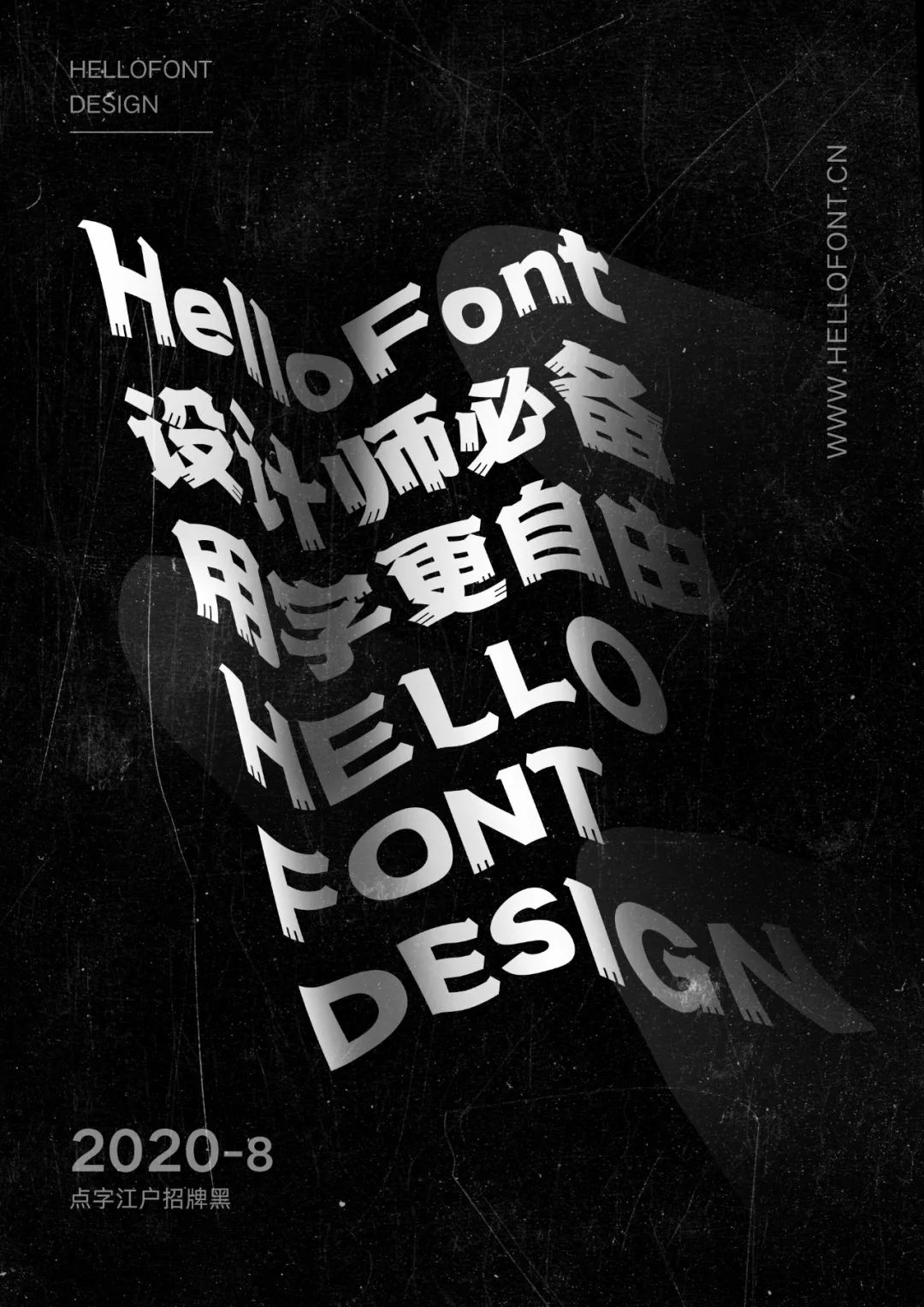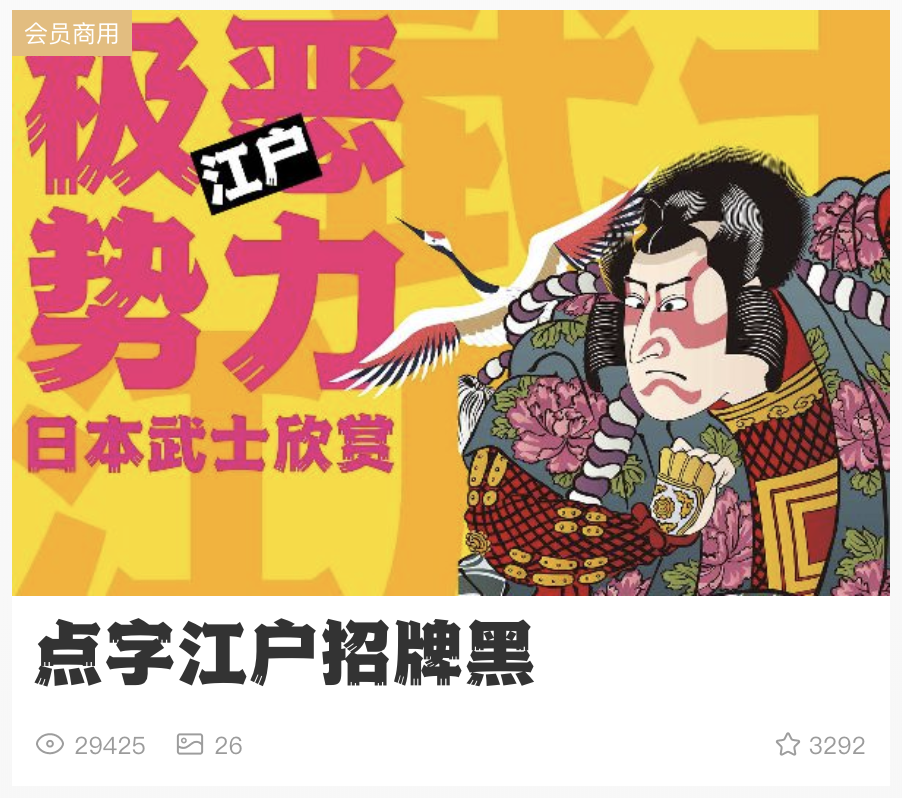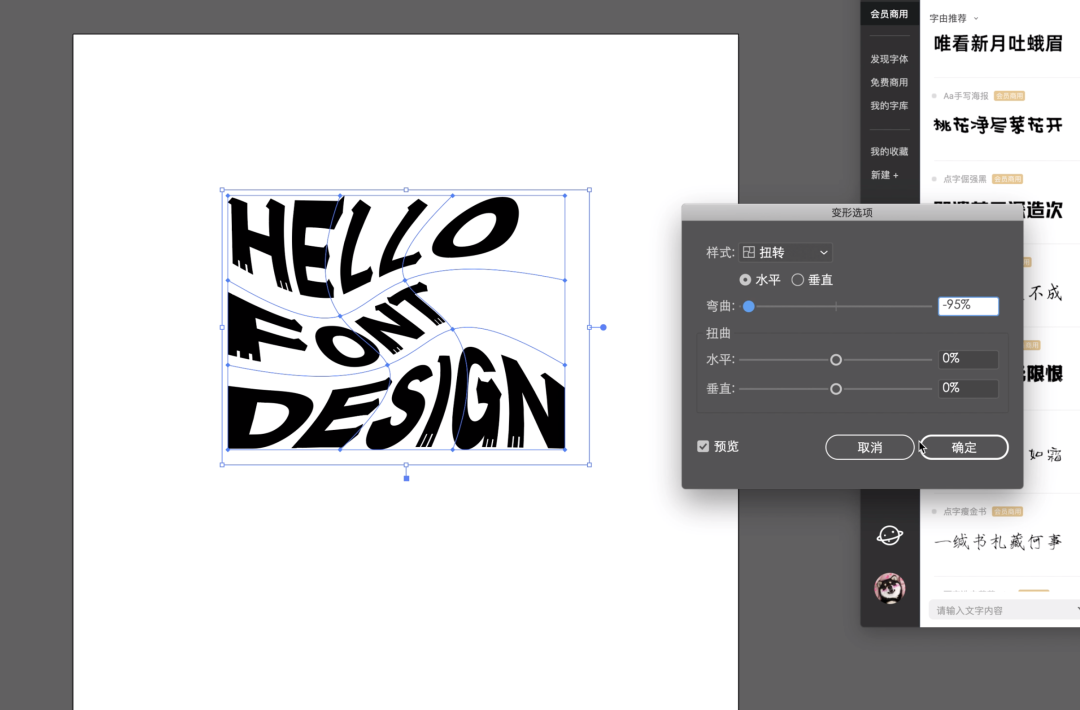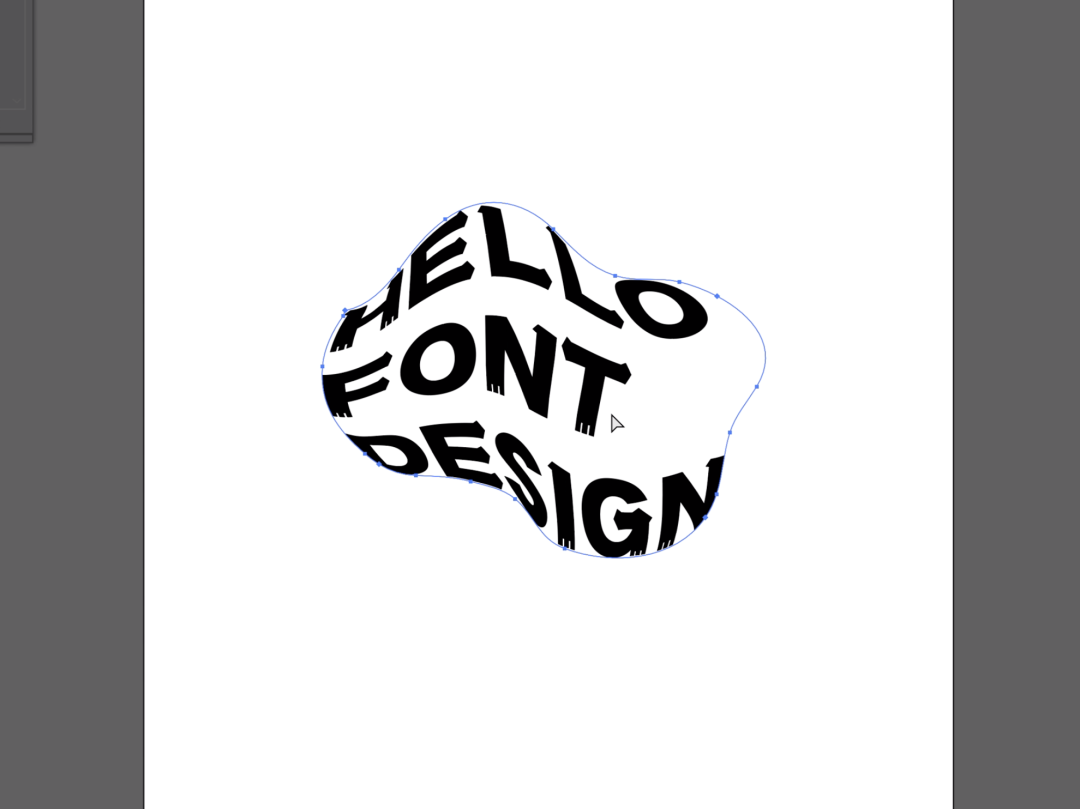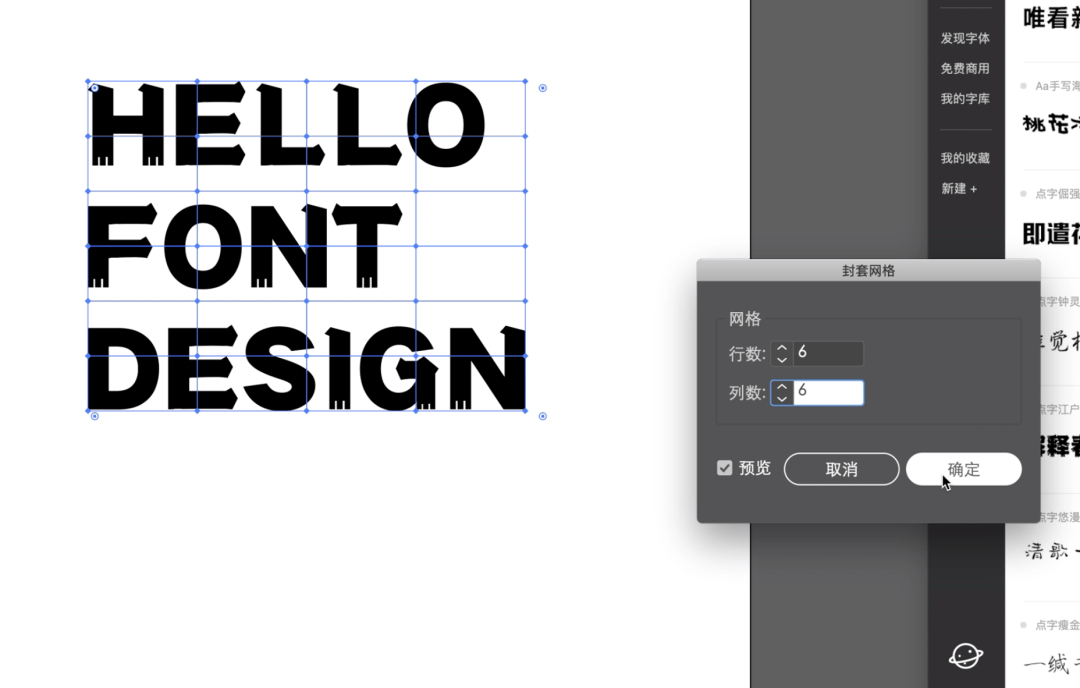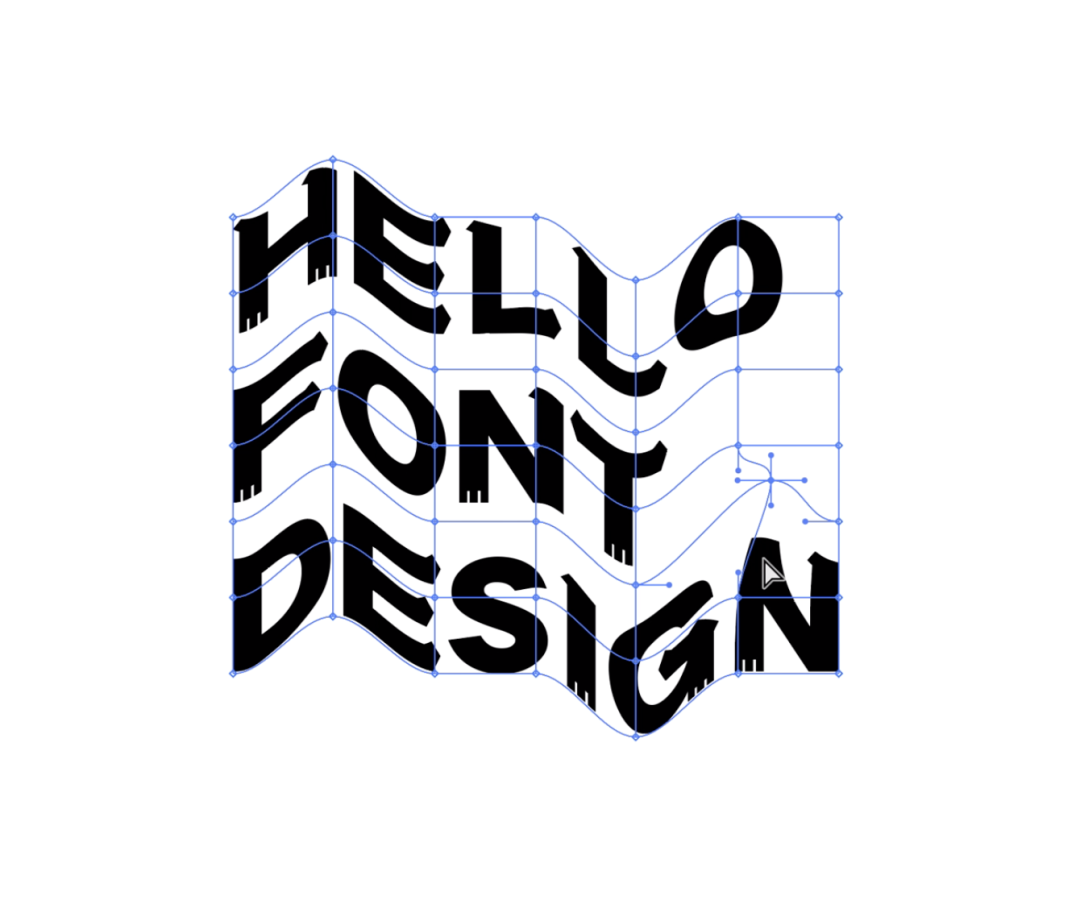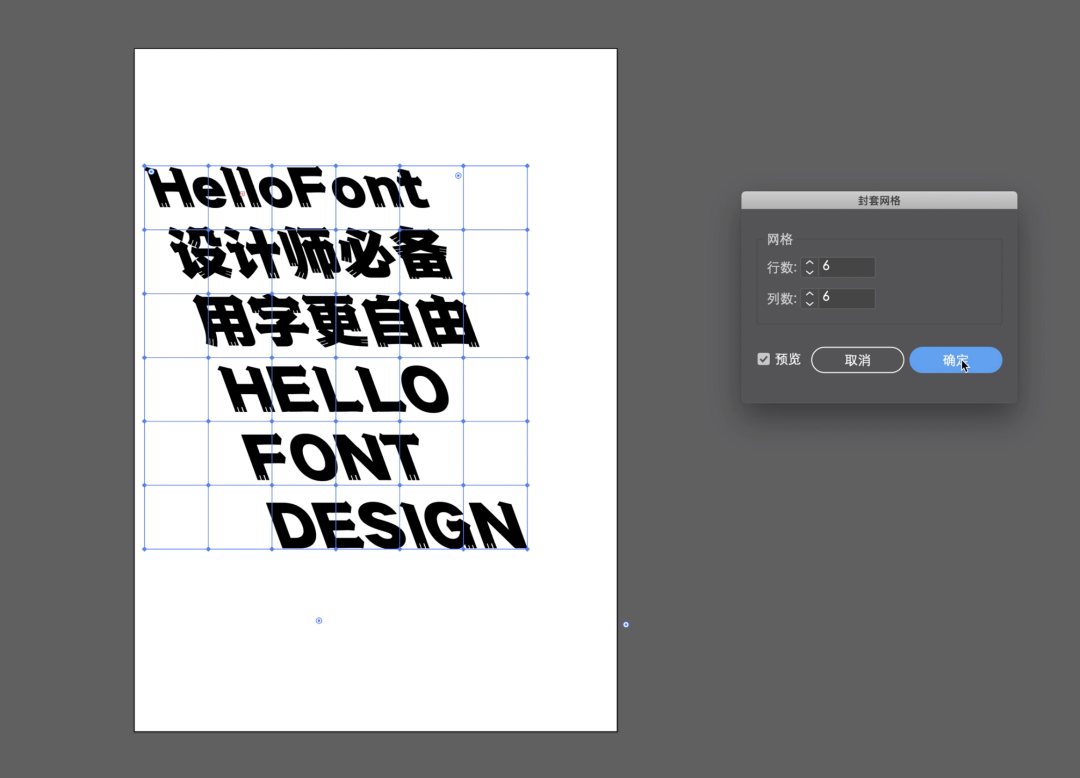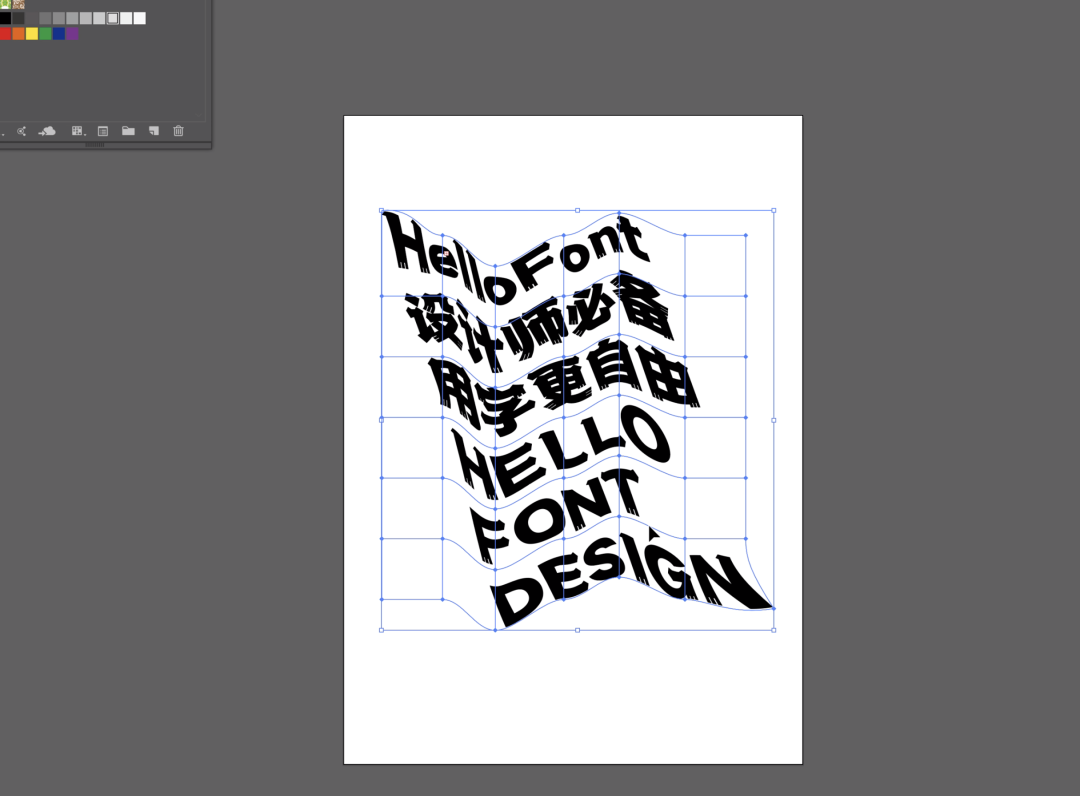
如何把字体“扭”出高级感?手把手教你三种方法
今天柚子要和大家分享一个能迅速提升设计感的小窍门:字体扭曲。虽然最开始一说到这个名词,总是会想到“老年人特效”……
说是字体扭曲的效果倒也没什么毛病
☠️
不对不对划掉划掉划掉
还是来康康字体扭曲正确的打开方式吧:
柚子也有样学样做了一张海报☺️
是不是还不错?那到底怎么做呢?首先要了解制作字体扭曲的三种方法。
方法一
先打上文案,这里柚子用的是点字江户招牌黑,比其他黑体字多了一点小细节,又能体现黑体的稳(逼)重(格)。
选中文本框,点击菜单栏-对象-封套扭曲-用变形建立。
样式选择弧形,数值可以自行设定。
也可以选择不同的样式,达到理想中的扭曲形态、扭曲方向和扭曲程度。
方法二
用钢笔或者画笔随便画一个闭合的形状,如果不闭合记得画完右键选择一下连接。
同时选择文本和刚刚画的形状,点击菜单栏-对象-封套扭曲-用顶层对象建立。
就能得到这样的效果~
方法三
选择菜单栏-对象-封套扭曲-用网格建立。
选择网格的行数和列数。
就可以手动进行字体扭曲啦~
海报教程
随便给海报文案排一下版,选择菜单栏-对象-变换-倾斜。
参数如图:
利用上面的方法三,封套扭曲-用网格建立,建立扭曲网格。
将文本制作成一种“水上漂”的感觉~
把做好的图拉到ps里进行后续的美化。
用柔边画笔在文字上画出明暗,增加立体感。
再在背景画一些小细节,调整一下位置。
最后根据喜好,在海报上叠加一层质感素材就大功告成啦!